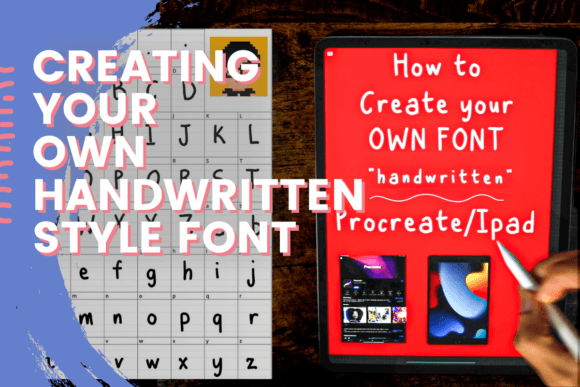
Creating Your Own Handwritten Style Font
Om du letar efter högkvalitativa tillgångar som Creating Your Own Handwritten Style Font, är detta premiumpaket ett fantastiskt val för dina kreativa projekt.
Oavsett om du skapar POD-produkter (Print on Demand), bröllopsinbjudningar eller grafik för sociala medier, är Creating Your Own Handwritten Style Font ett perfekt val.
Experttips: Kombinera dessa element med kompletterande typsnitt för att skapa unika, iögonfallende mönster som sticker ut.